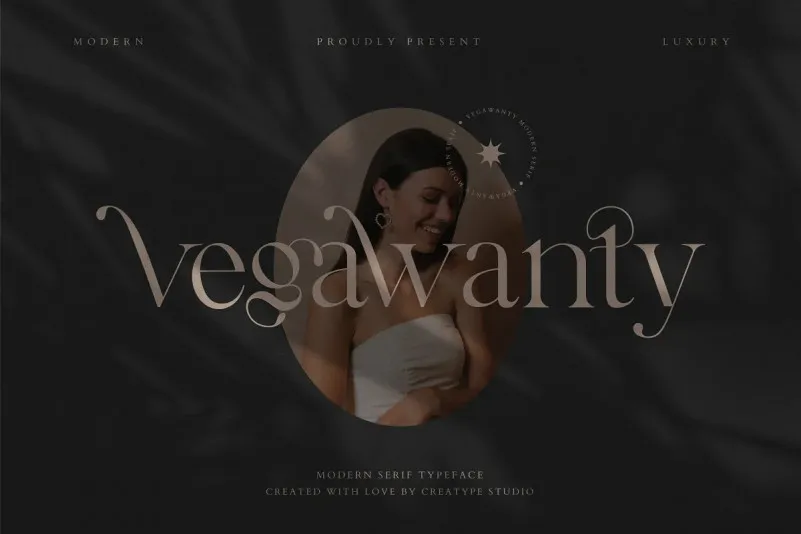
A Vegawanty Font é uma serifada clássica e moderna que traz uma variedade de ligaturas para tornar qualquer design mais elegante e sofisticado. Esta font foi criada pelo Creatype Studio e compartilhada com o mundo através da plataforma 99designs. Suas formas redondas e finas oferecem um equilíbrio entre clareza e detalhes, fazendo do Vegawanty uma escolha ótima para designer de produtos que desejam dar seu trabalho design a um toque mais elaborado. Com suas linhas sólidas e suaves, essa serifada traz uma personalidade única ao texto, tornando qualquer projeto notável. Não perca tempo, transforme suas criações em algo extraordinário com Vegawanty Font.